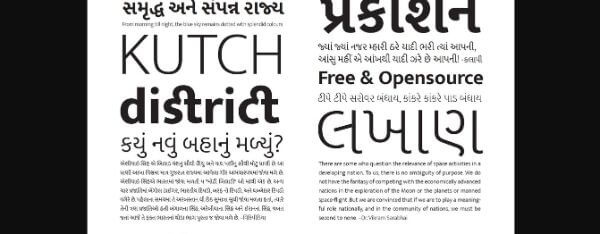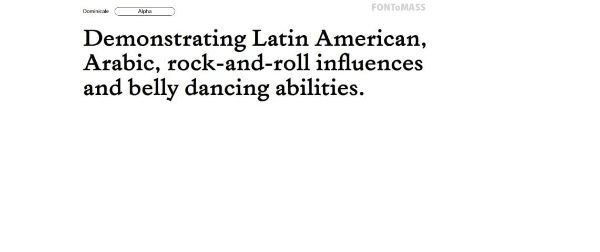
あなたが選んだフォントは、あなたのプロジェクトについて多くの事を教えてくれます。そして、見ている人の印象を決めます。これは、多言語の国の人を対象にしている場合、重要になります。この場合、同じ内容を複数の言語で伝える為に、多言語に対応したフォントを使わなければいけません。例えば、ターゲットがインドの場合、インドで何種類の言語が使われているか知る必要があります。そして、良い印象にする為に、それぞれの言語に合わせたフォントを選ぶ必要があります。
さらに、人は住んでいる地域や母国語で書かれているものに好感を持ちます。色々な国で、複数の言語を話す人がいます。なので、それに対応する為に、多言語で使えるフォントを集めました。それらのフォントを紹介していきましょう。
1. Grotte:
Grotteは、スペイン語、ポルトガル語、ドイツ語、デンマーク語、キリル文字に対応しているフォントとして有名です。複数の言語に対応した高いフォントのパッケージを買う必要はありません。これは、無料でたくさんの言語に対応しています。 Grotteは、美しい幾何学模様のサンセリフ体フォントです。
ここにあるフォントは、曲線で作られていて、何に使っても上品になります。なので、自然で清潔感のある仕上がりになります。Grotteは、ポスター、パッケージ、コマーシャルなどに使えます。国際的なマーケティングキャンペーンで予算が少ない時、ここのフォントが役立ちます。
2. Omnes:
飲料会社のコカコーラ社は、ファンタという商品の宣伝に、ここのフォントを使いました。その結果、私達に可愛い印象を与えました。調味料を扱う会社でもここのフォントが使われ、ここのフォントは一般的になりました。 Omnesは、丸みを帯びた太字のフォントで、味覚に訴えかけます。
なので、食品関係のプロダクトをデザインする時に、このフォントが使えます。このフォントを使うと、説明しなくても味を想像できるようなデザインができます。Omnesは、アフリカ語、ポーランド語、ラテン語、ソルブ語などに対応しています。無料でダウンロードできます。
3. Helvetica World:
Helveticaはデザイナーやウェブ開発者に人気です。なぜなら、綺麗で清潔感あるデザインになり、プロが作ったような仕上がりになります。 しかし、Helveticaは色々な所で使われているので、他のものを使いたくなるかも知れません。 もし、ターゲットが世界中の人か、多言語を話す人の場合、Helvetica Worldのフォントを選ぶといいです。
Helveticaは、ライノタイプの進化版です。 Helvetica Worldは102の言語に対応しており、多言語を話す人達がターゲット層の場合に最適です。 融通性があるので、使いやすいです。上のリンクからダウンロードできます。
4. Suisse:
Suisseはスイスで作られた字体です。55の違う形が入っている、6種類の字体があります。綺麗ですっきりとしたデザインで、複数の字体を組み合わせてデザインする事ができます。ラテン語、キリル文字、アラビア語などにも対応しています。
もし、すっきりとしたフォントの簡易版がいいと言う時は、Suisse Monoか Suisse Condensedを試してみてください。 どのフォントを使うか決める前に、必ず一度試してみて、他の人に見てもらい、どう思うか聞いてください。
5. Dominicale:
Dominicaleはスラブセリフ体で作られた、変わったデザインでスッキリとしたフォントです。古代を思わせるような仕上がりになります。中世の古典文学を扱っている人達に使われています。
角ばったフォントで、ポスターやパッケージのデザインに合います。 このフォントは、英語、フランス語、ドイツ語に対応しています。Hence, Dominicaleは、ヨーロッパの人達をターゲットにしている時、使うといいです。
6. Gill Sans Nova:
このフォントは、1928年からずっと、グラフィックデザイナーやウェブデザイナーに選ばれています。各出版社は、多くの出版物にこのフォントを使っています。
イギリス風のフォントですが、色々な言語に対応できるパッケージです。Gill Sans Novaは2015 年に、Monotype社の年間表彰を受けました。 in the year and had ラテン語、ギリシャ語、キリル文字に対応した43のフォントがあります。
7. Greta Sans:
Greta SansはPeter Bilakが作ったフォントです。そして、Typothequeのサイトに最初に載ったフォントです。Greta Sansは、力強いフォントで、10の重量と3種類の大きさがあります。これらは、色々な絵文字に使え、 217の言語に対応しています。
融通性があり、ヘブライ語、タイ語、韓国語などにも使えます。色々なプロジェクトで使えます。複数の国を対象にした、国際的なプロジェクトに有効です。これらのフォントを使うと、ターゲット層に伝わるので、顧客の反応を心配する必要が無くなります。
8. Google Noto:
「Noto」は「No Tofu」という意味です。 Tofuは、あなたのデバイスに対応していないフォントを見るためのものです。Tofuの欠点を補うために、グーグルは、全ての言語に対応できる Google Notoを発表しました。これを使うと、tofuを使わなくても色々なフォントを見る事ができます。
Notoは、ほとんどのフォントの容量や形に対応しています。無料でダウンロードできます。あなたは、ウェブサイトから必要なフォントをダウンロードするだけです。サイトでフォントの詳細を見ると、そのフォントがどの地域で使われているかわかります。ここで、あなたのターゲット層にはどのフォントを使えばいいのかわかります。
9. SST:
SSTは、Sony CorporationとMonotype GmbHのジョイントベンチャーで作られたフォントです。ソニーはこのフォントを公式に使っています。これらのフォントは、どこで使っても綺麗で上品な、プロが作ったような仕上がりになります。このパッケージには、色々な容量や形のフォントが入っています。
さらに、SSTはロシア語、セルビア語、マケドニア語、スペイン語、スウェーデン語、ノルウェー語、フランス語、ドイツ語、アルベニア語など 35 の言語に対応しています。これらのフォントを使うと、力強いイメージになります。なので、見た人の注目をひき、ナンセンスな印象にしたくない時に最適です。
10. Misto:
Mistoはウクライナ語で「町」という意味です。 Mistoのフォントは、まだ出来て32年しか経っていないウクライナの都市スラブチッチで作られました。
これらのフォントは、ストローク形式で作られています。Mistoは、ラテン語とキリル文字に対応したサンセリフフォントです。なので、ターゲット層がこれらの言語を話す人々の場合、これらのフォントが合います。
11. Restora:
Restoraは、Nasir Uddinが作った セリフフォントの一つです。Restora は、レトロ風のセリフフォントを元に作られた、変わった形のフォントです。汎用性があり、どこででも使えます。
Restoraには、スモールキャップやレトロ風の数字なども入っていて、730以上のグリフがあります。このフォントは、西ヨーロッパ、ヨーロッパの中・東部地域、バルト海地域、トルコ地方、ルーマニア地域の言語に対応しています。
12. Okta Neue:
Okta Neueは、2019年に作られたOktaの一種類です。これらのフォントは、見やすい幾何学的なデザインで、ストローク間の抑揚が少なくなっています。Okta Neueは、多くの言語に対応する目的で作られました。
なので、Okta Neueは、キリル文字、ギリシア語、ヘブライ語、ブルガリア語、セルビア語などにも対応しています。このフォントは22種類の変わったデザインです。これを使うと、このプロジェクトが何なのかわかりやすくなります。
13. Argesta:
Argestaは、セリフフォントの一種類で、 昔からある形です。これらのフォントは、豪華でヴィンテージな雰囲気に合います。Argestaはオートクチュールを元に作られているので、ターゲット層がオートクチュールが好きなら合います。
パッケージのデザインを、豪華で上品な雰囲気にしたい時にも使えます。無料でダウンロードできます。
14. Disket Mono:
Disket Monoは、Mariano Diezが作ったディスプレイ用のフォントです。これらのフォントは、モジュラー系の格子柄が基本になっていて、幾何学的で近代建築のようなデザインになっています。Disket monoには、614種類の一般的な太字が入っています。
色々な言語に対応しているので、使う人が増えてきました。もっと言うと、20の言語に対応しています。ロゴのデザインや プロモーションに最適で、他にも色々な所で使えます。
15. Butler:
Butlerは、 Dala FlodaとBodoniを合わせた美しいフォントのセットです。これらのフォントは、セリフフォントが作られた時代を思い出させるような雰囲気のセリフフォントです。さらに、ステンシルフォントを追加する事ができます。
これらのフォントは、本のタイトル、ポスター、実用品などに使えます。 Butler fontは、 334種類の形と、7つのフォントの容量があります。 7種類のステンシルフォント、テキストの図形、フラクション、連字なども入っています。グリフを加えると、多くの言語に対応できるようになります。
16. Bagnard:
Bagnardは、Doug Thomas、Chris Fodge、May Kimの3人のデザイナーがそれぞれ違う種類のセリフフォントを作ったものです。これらのフォントは、オープンソースになっていて、無料でダウンロードできます。Bagnardのフォントは、傾きがはっきりしていて、ブラシで書いたタイプフェイス に似ています。
なので、これらのフォントは見た人の注目を集めたい時に使うといいです。 Bagnardは多くの言語に対応していて、色々な形があります。 なので、グラフィックデザインなどで、よく使われているフォントの一つです。
最後に
最新の タイポグラフィは、多言語に対応しているのが標準です。世界中に発信したい時は、多言語に対応している事が必要です。多数の顧客をターゲットにしたい時は、多言語に対応しているフォントが必要です。内容が文字だけだと、荘厳には見えません。
そのような場合でなければ、多言語に対応したフォントを用意する必要があり、その前にターゲット層の言語を知っておく必要があります。そうすると、どのフォントを使えばいいかわかります。使うフォントとどこをターゲットにするかをはっきりすると、半分成功したようなものです。